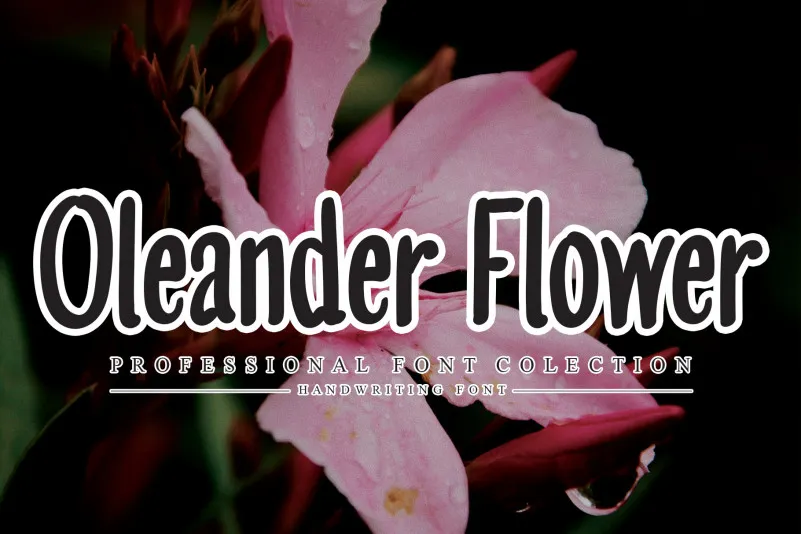
Oleander Flower Script Font – Download Grátis
A fonte ‘Oleander Flower Script Font’ é uma opção ideal para aqueles que procuram um estilo simples e elegante, perfeitamente adaptado ao mundo do design gráfico. Ideal para quem busca uma fonte escrita a mão, sua natureza delicada e suave permite criar designs impressionantes e únicos. Seja para aplicativos de mídia social ou criações de marca, ‘Oleander Flower Script Font’ é perfeita para adicionar um toque autêntico à sua produção. Esta fonte é uma escolha ideal para designers que valorizam tanto a simplicidade quanto a delicadeza. Proporcionando a você e ao seu público um design único, esta elegante fonte escrita a mão vem da designer andikastudio, que oferece uma variedade de opções. Seja você criando cartões de visita, editoriais de moda ou desenhos digitais, ‘Oleander Flower Script Font’ pode transformar seu trabalho em algo realmente especial.